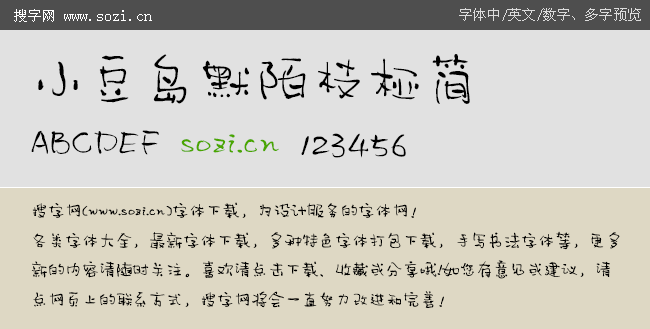
小豆島默陌枝椏簡
搜字網(wǎng)提供一款小豆島默陌枝椏簡中文字體下載,小豆島默陌枝椏簡是一款帶有卡通風(fēng)格的手寫書法字體,這款字體充滿童真,趣味十足,整體效果非常可愛,適合應(yīng)用于兒童海報(bào)設(shè)計(jì)、書籍裝幀、畫冊(cè)封面、產(chǎn)品包裝設(shè)計(jì)等應(yīng)用。